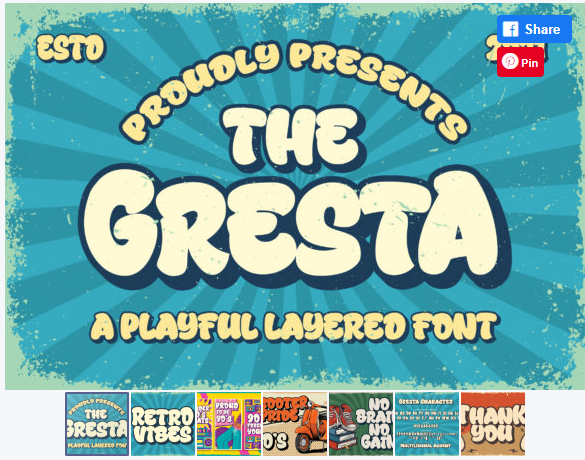
[Creativefabrica] Gresta Font (Blankids Studio)
Gresta - это смелый, игривый и веселый шрифт. Если вы используете его для дизайна, связанного с мультфильмами, детскими играми или просто для любого творения, требующего милого прикосновения, этот шрифт станет прекрасным выбором.